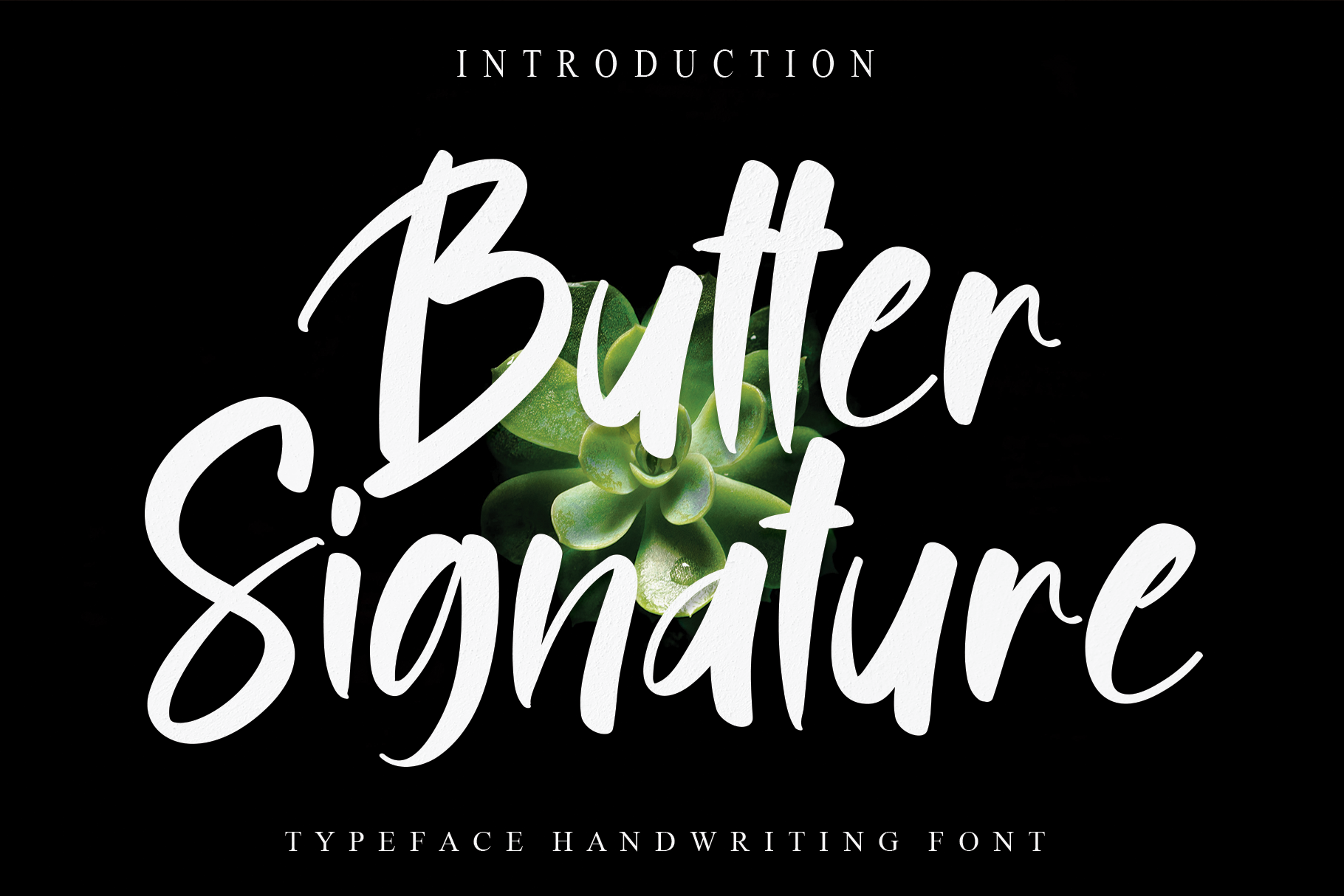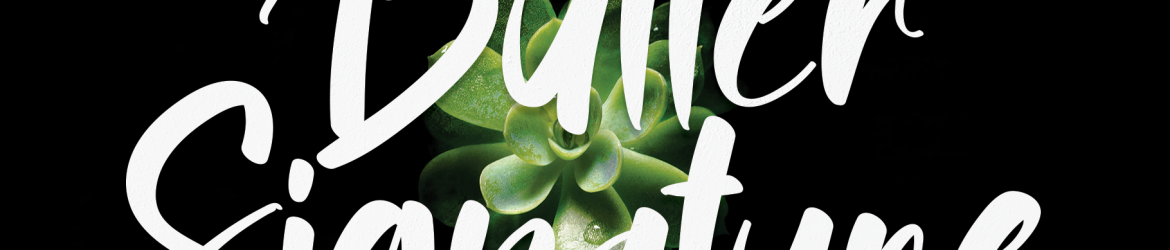
Butter Signature Font – Download Grátis
Esta é uma fonte script divertida e descontraída. Com aplicabilidades que vão desde cartões de felicitações até headlines, essa fonte é versátil. Ideal para adicionar um tom alegre e revitalizador à próxima iniciativa. Como designer creativeletter sugeriu, ela pode enriquecer projetos digitais ou impressos com uma sensação amigável e reequilibrada. Esta fonte script de qualidade será uma escolha inteligente para qualquer trabalho que busque personalidade e frescor. Descubra a versatilidade dessa criação criativa e explore as infinitas possibilidades da design type.